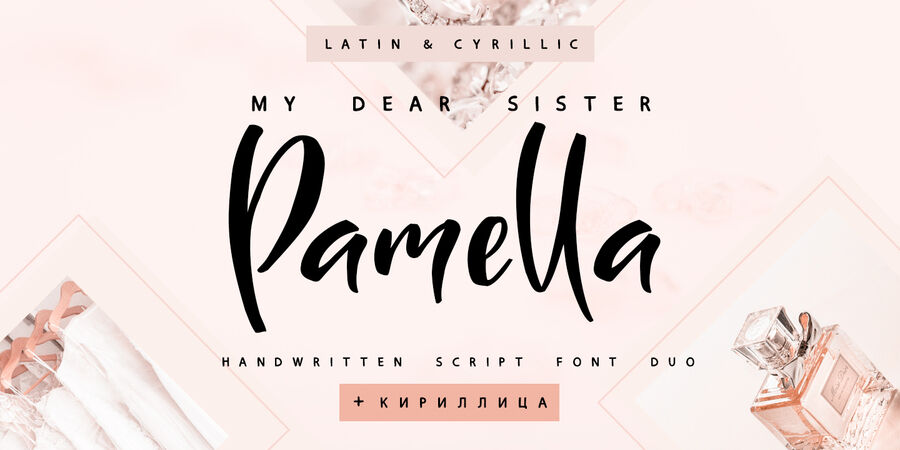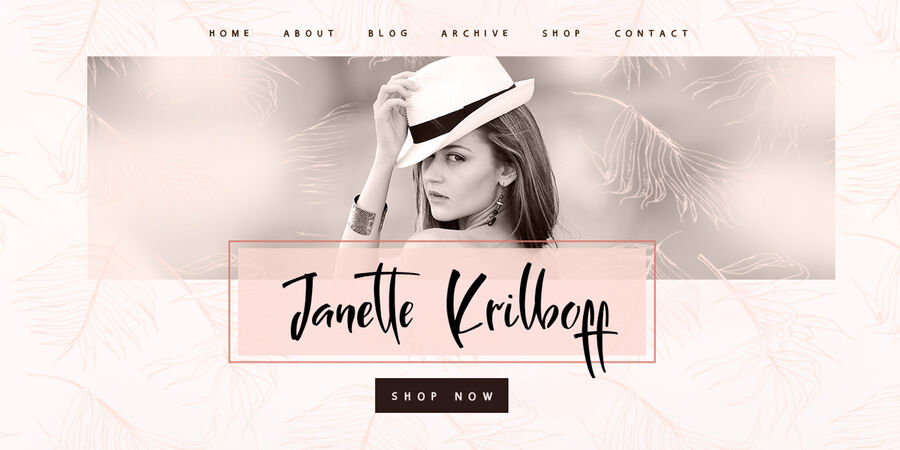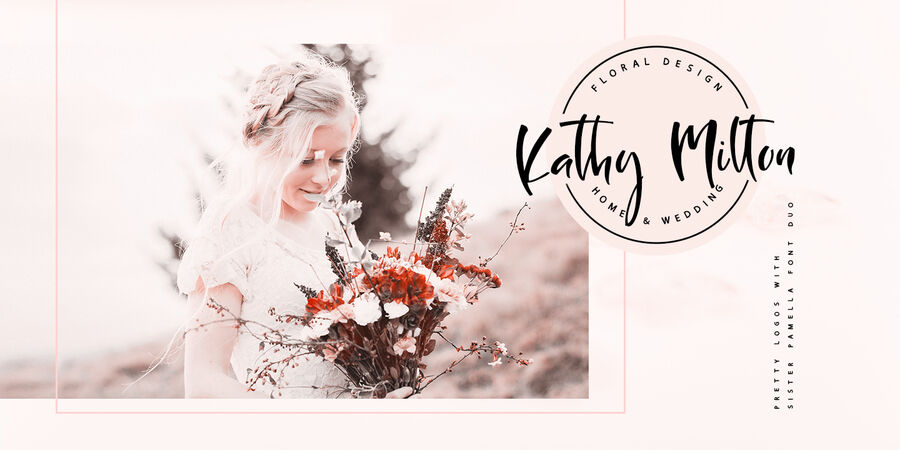
Це рукописний шрифт з шрифтової пари Sister Pamella Font Duo Cyrillic яка в поєднанні ідеально підходить для використання у всіх ваших дизайнерських проектах, будь то логотипи, підписи, етикетки, дизайн пакування, заголовки блогів. Крім того, він буде мати гарний вигляд на кухлях, вивісках, листівках, типографічних плакатах, весільному канцелярському приладді й багато іншого. Sister Pamella Script містить повний набір великих літер, 2 набори малих літер, цифри, великий діапазон розділових знаків і 38 лігатур, що створює реалістичний стиль літер, написаних від руки. Багатомовна підтримка 31 мови на основі латинки та кирилиці.
Шрифт розробила Ірина Двілюк у 2021 році.
Асоціації з сімейством шрифтів Sister Pamella ScriptОсобистість і характер гарнітури:
швидкий, артистичний, органічний, динамічний, свіжий, неохайний, веселий, легковажний, емоційний, рідкий, лихий, рухливий, непосидючий, мультяшний, яскравий, смачний, смішний, добрий, милий, М'який, ремісничий, рукотворний, ручний, доброзичливий, довірчий, зелений, натуральний, природний, грайливий, потішний, прикольний, живий, оригінальний, привітний, характерний, святковий, соковитий, стиглий, крафтовий, радісний, пустотливий, весняний, літній, щасливий, стрибучий, танцюючий, моторний, вільний, розмашистий, модний, сміливий, цікавий, енергійний, темпераментний, самобутній, художній, мрійливий, виразний, помітний, творчий, експресивний, активний, романтичний, приємний, красивий, дівчачий
весна, кафе, інтер'єр, квіти, подарунки, хенд мейд, їжа, відпочинок, природа, анімація, мультфільм, торгівля, розваги, живопис, фарби, кава, Інстаграм, косметика, краса, мода, одяг, закуска, танець, музика, ресторан, свято, Новий рік, золото, виставка, селфі, романтика, графіка, ілюстрація, мистецтво, захід сонця, вечір, пейзаж, акварель Гарнітура має ознаки стилів: